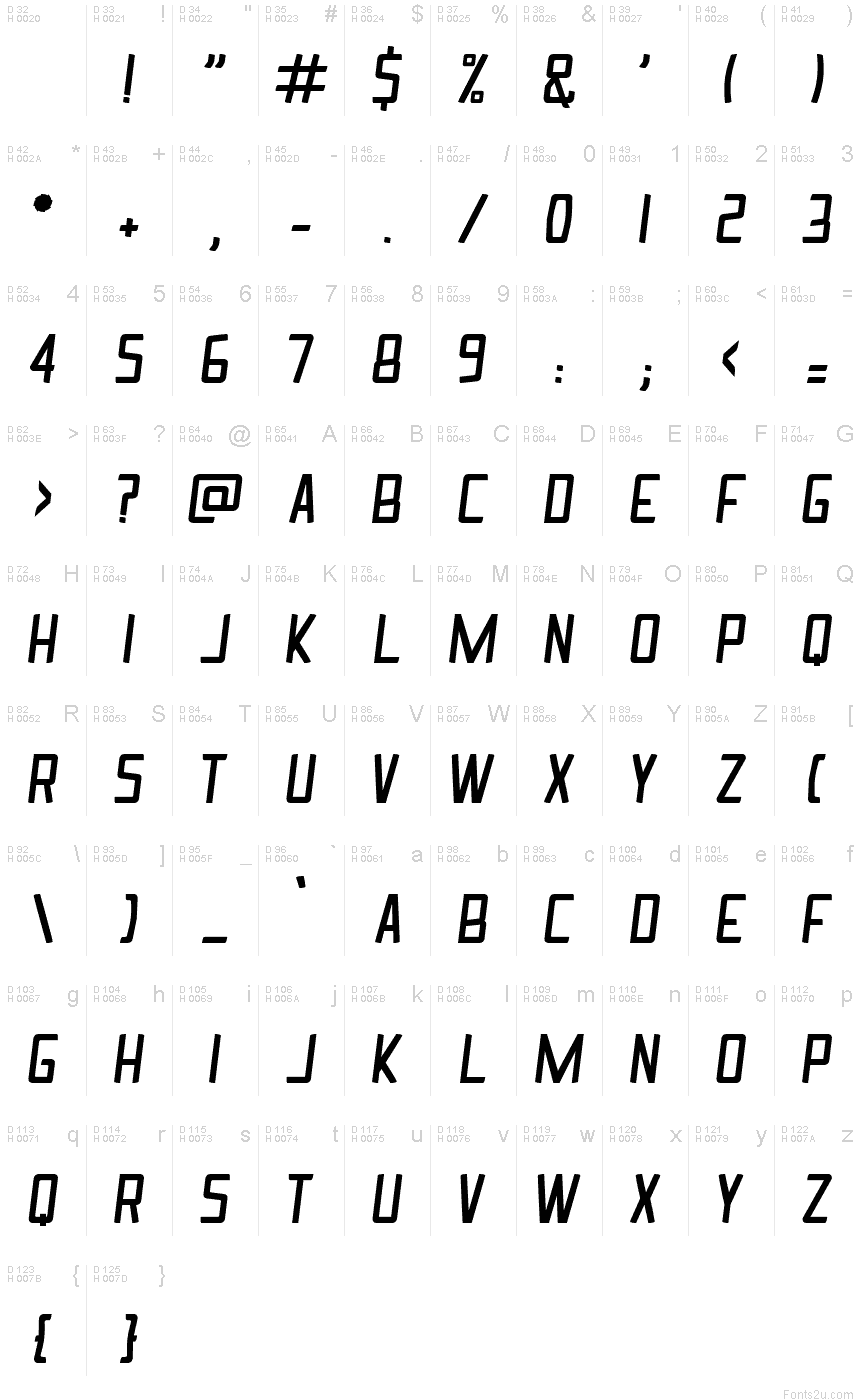
Ingrata-Italic
aFalange|estdio.ElvisH.Martuchelli-ViniciusdeAbreuLima-RicardoJacobHessel: Ingrata: 2005
Set tipogr?fico criado para a conclus?o de semestre da disciplina de Tipografia da Universidade Anhembi Morumbi. Fonte elaborada sob a orinta?nao do Prof. Tadeu Costa ? quem somos muito gratos pela paci?ncia. S?o Paulo - Brasil - 2005/2.